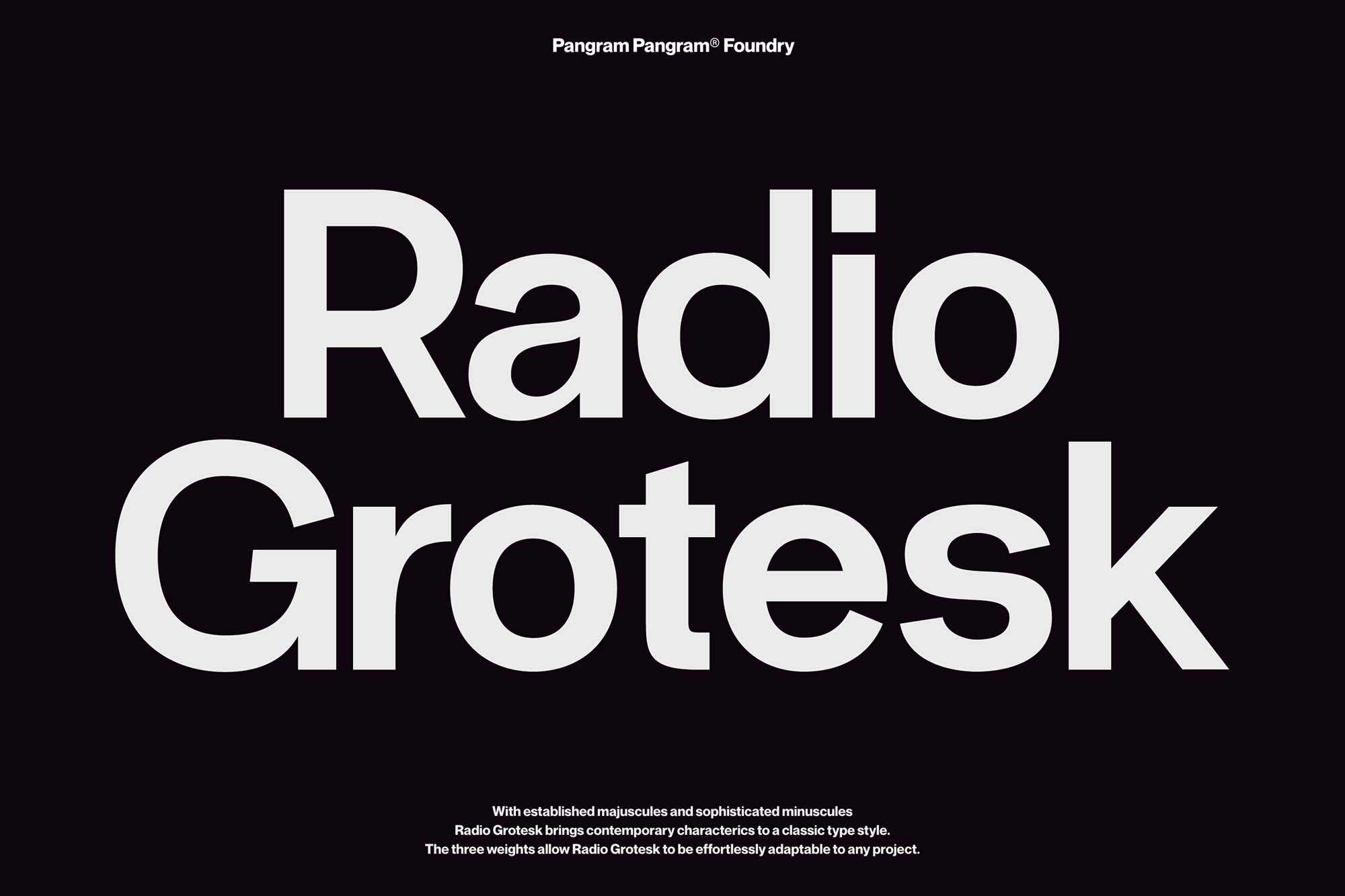
Este estilo de fonte Grotesk Sans oferece três pesos, leve, regular e bold, e a fonte de demonstração está disponível gratuitamente para uso pessoal. O famoso Radio Grotesk font family apresenta uma aparência clara e reta, que é ideal tanto para materiais corporativos quanto para marcas de estilo contemporâneo. Ideal para estilos de vida modernos e corporativos, a Radio Grotesk se destaca com sua força e simplicidade, uma característica que a torna uma opção popular em qualquer aplicação gráfica. Seja em postagens de mídia social, materiais de marketing ou até mesmo em aplicações digitais, o Radio Grotesk garante um design limpo e moderno. Não perca essa oportunidade de adicionar uma fonte de qualidade a seu arsenal gráfico.